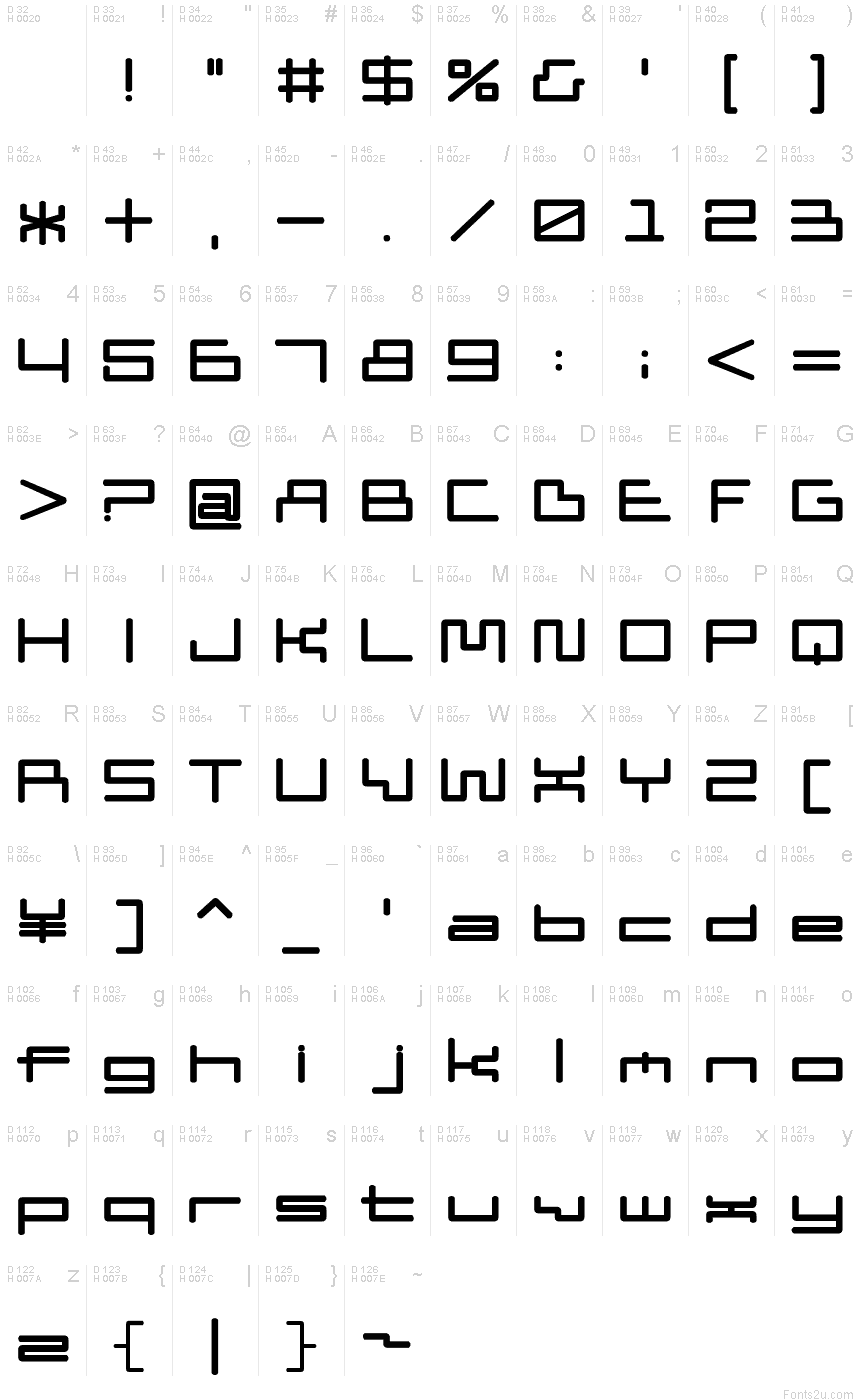
خط D3 PipismW من تصميم Yoshiyasu Ito هو خط تقني (Display) مجاني يتميز بإيقاع انسيابي وأنبوبي يشبه أنابيب النيون المنحنية على شكل مستطيلات ناعمة. تتميز كل حرف بضربات سميكة ومتجانسة، مع زوايا مستديرة وخطوط مزدوجة متفرقة توحي بمسارات الدوائر الإلكترونية. الانطباع العام مستقبلي ولكنه ودي، مع مساحة كافية بين الأشكال للحفاظ على وضوح القراءة حتى عند تقارب الحروف.
يتألق هذا الخط المجاني في شعارات الألعاب، وملصقات الخيال العلمي، وأغلفة موسيقى التكنو، ومنشورات الفعاليات التقنية، وشاشات تشغيل التطبيقات، وأي تصميم تجريبي يحتاج إلى نبرة نظيفة وغير تقليدية. استخدام D3 PipismW بأحجام كبيرة يبرز جمال أشكاله الانسيابية الأنبوبية، بينما يساهم دمجه مع خط هندسي بسيط بلا زوائد (Sans) في النصوص الأساسية في الحفاظ على مظهر حاد وواضح للتصاميم.